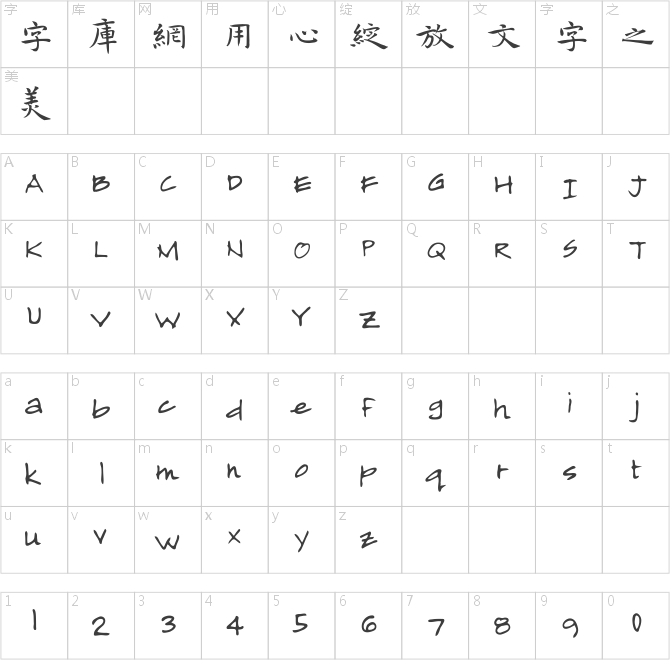
楷書
五臺楷書,由“生活禪”先行者本覺上人在五臺山修持時主導設計、制作的一套楷書字體。集體成庫,發行流通,惠施大眾,同品禪韻。 五臺楷書,溯源于禪心,師法于禪門機鋒古趣,含八大山人之瀟灑自在;俱弘一法師之圓融潔凈。顯修證者抵心源之寂寂,涌自性之妙趣!以禪入墨,似本覺朗照之孤明無際;以墨寫心,如流芳大千之妙用恒沙!五臺楷書,細細品之,似文殊持慧劍斬絕翳穢,如觀音灑甘露普施清涼,滌人心肺,濾人思緒。